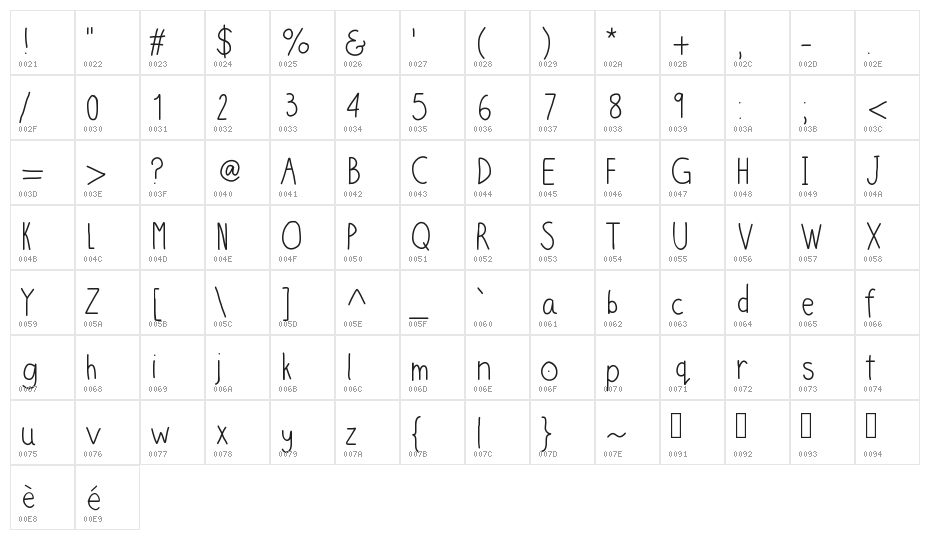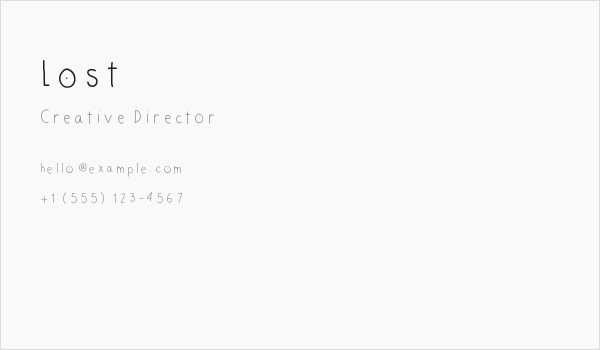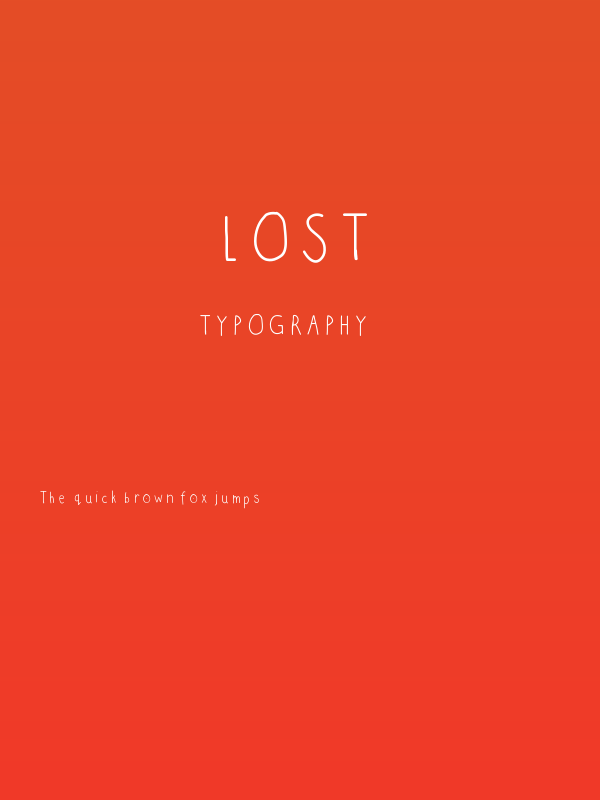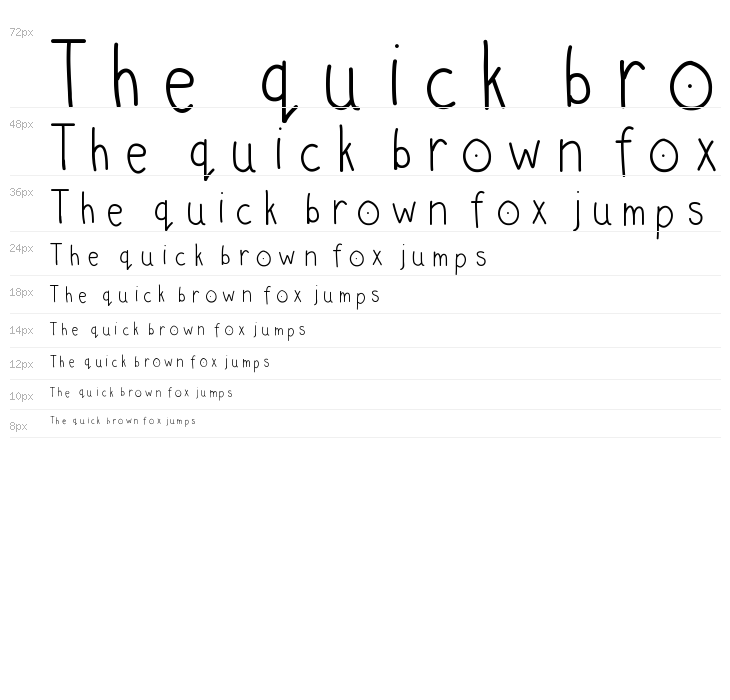
Lost Font
| 全体的なスタイル | Casual, Playful |
| 用途 | Headlines, Informal text, Creative projects |
| おすすめプロジェクト | Perfect for greeting cards, children's books, casual invitations, and playful branding. |